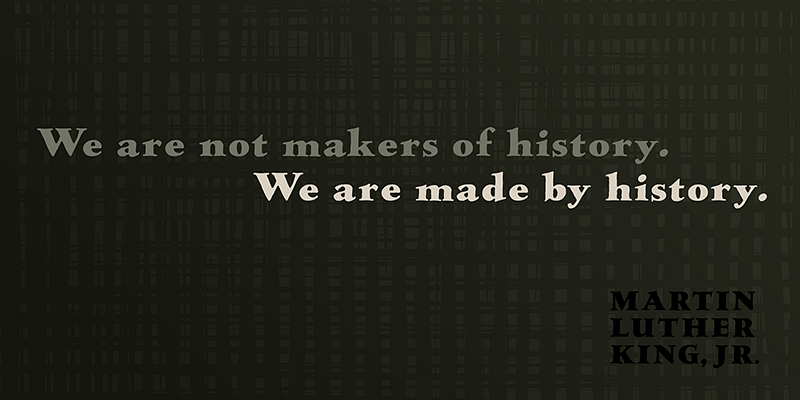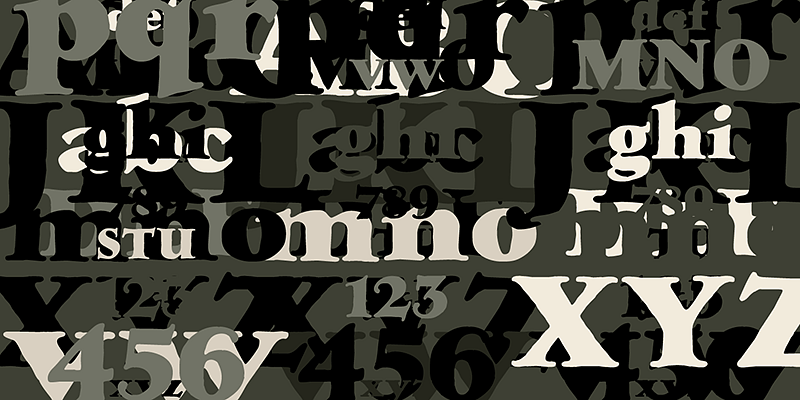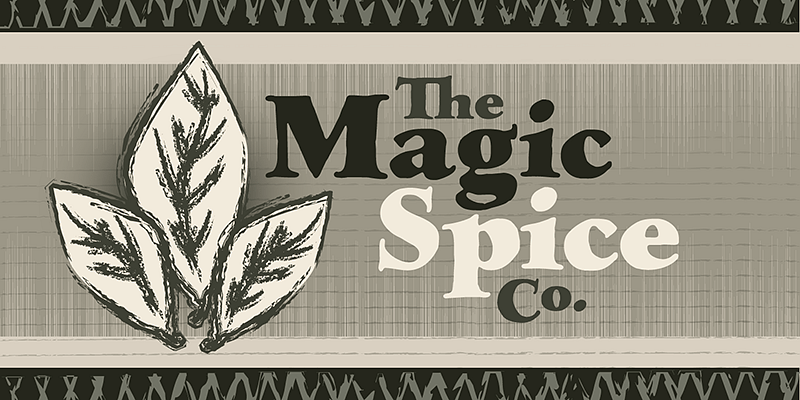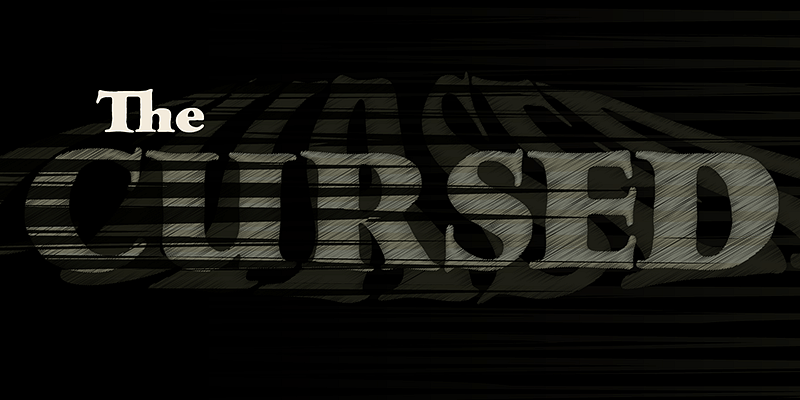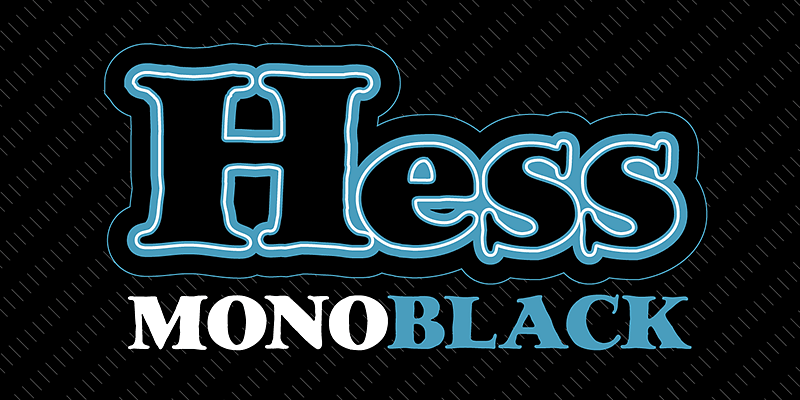
「LTC Hess Monoblack」は希少な金属活字で、「Lanston」の組見本にほんの少し登場しただけです。実際には金属活字の見本は存在しないようです。重厚感があり、見出しやパッケージに適しています。
Lanston Type Co. (LTC) のルーツは、モノタイプ鋳造機の発明者 Tolbert Lanston によって 1887 年に設立された Lanston Monotype Company に遡ります。英国の同業者と袂を分かった後、LTC は苦戦し、American Type Founders、Hartzel Machine Works、Mackenzie & Harris、Gerald Giampa に何度か売却されました。P22 Type Foundry は 2004 年にこの施設を買収し、現在は Frederic W. Goudy と Sol Hess の古典的なデザインと、新しい現代の巨匠 Giampa、Jim Rimmer、Dave Farey の本拠地となっています。